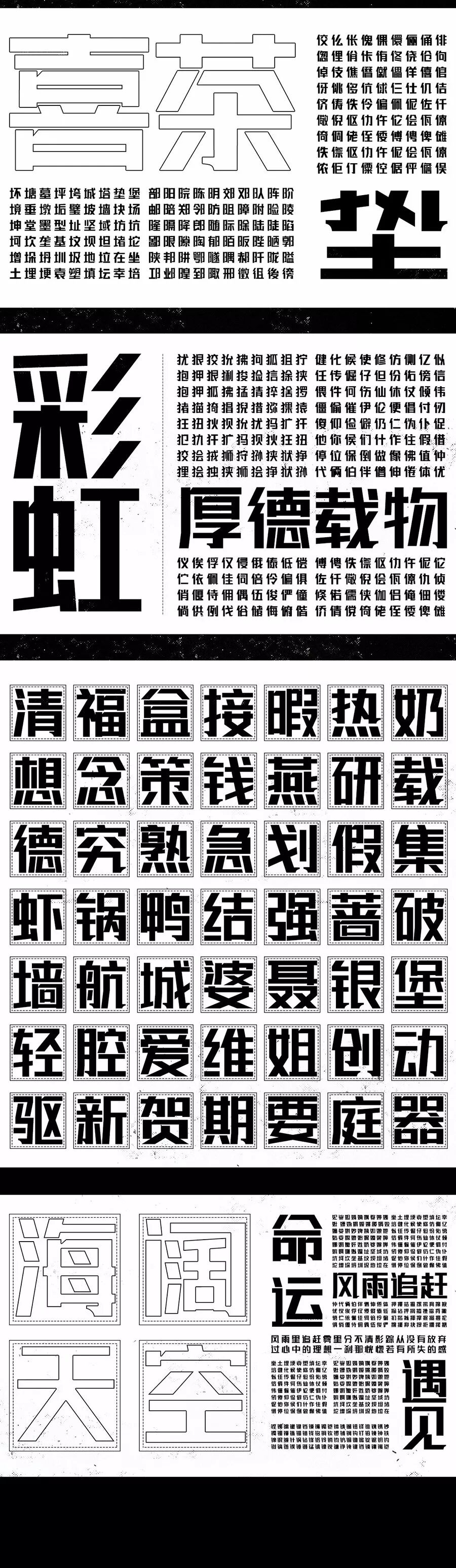
联盟起艺卢帅正锐黑体
联盟起义卢帅正锐黑体共计8000余字,永久免费商用标题体!字库团队骨干设计师:凌旬(徐文博)、子轩、璐过炒米(李璐)、尚伟、小呆瓜(黄鑫)、狮子(郭培晟)、吕少惠
字体班字库参与学员:周春、高翔、蒲永超、莫明潮、郑小慧、王欣旻、曾斯纯 、岳胜杰、沈光瑞 、吴伟 、杨康、卢凌锋、谭诚计、任燕凌、彭朝、郑莹、陈志娇、何继罡、林文姚、关倩、刘延振、黄文杰、詹勋铎、洪倩、黄美金、崔欣宇、刘宝玉、宋佳芸、刘璋、徐天琪、夏龙、种毛妮、李思、王国帅
整套字库开发历时近6个月,从2018年11月开始,到2019年4月才算真正完成,将近8000字!
主要适用于标题应用,电商、产品包装、海报招贴等,应用面非常广。